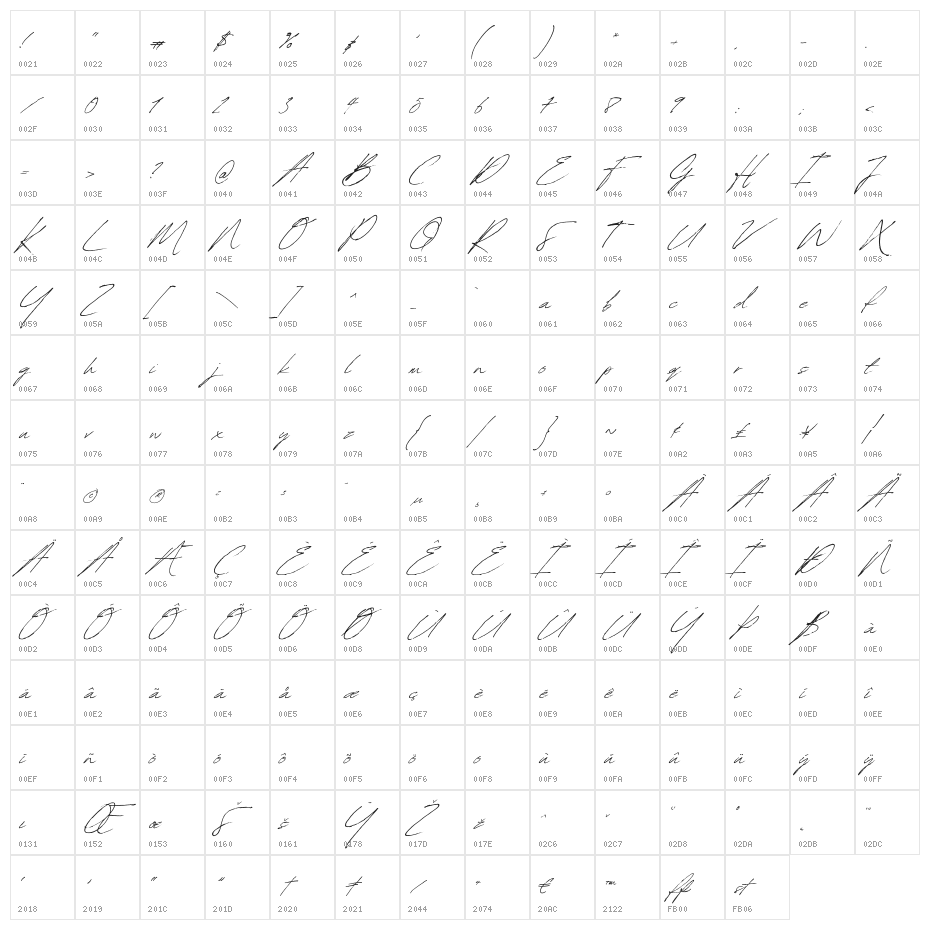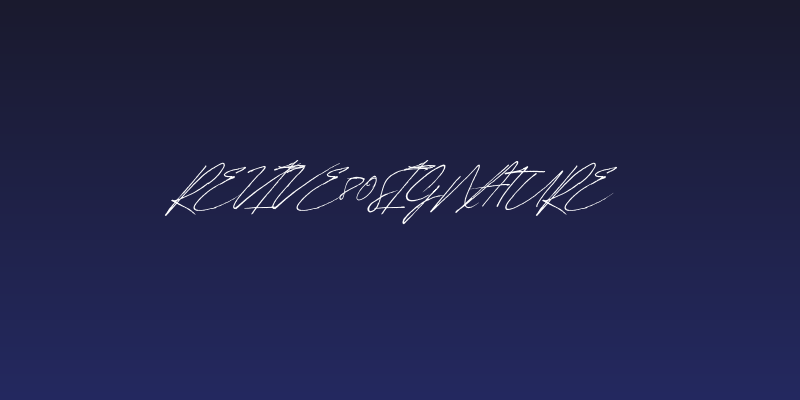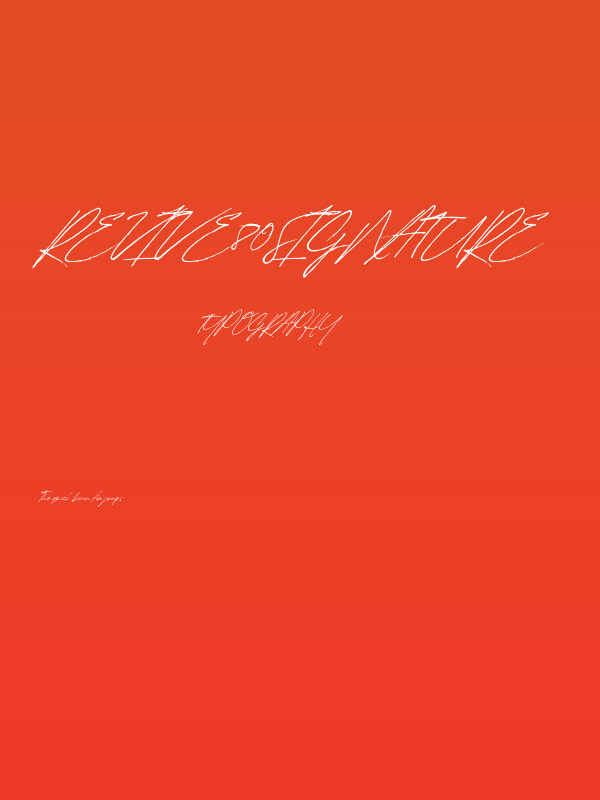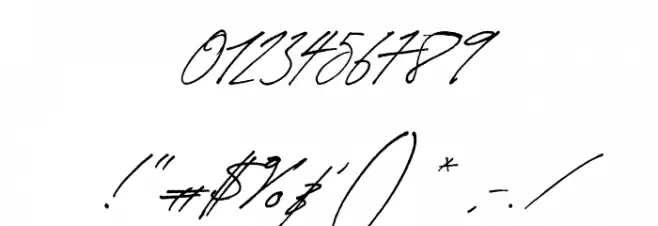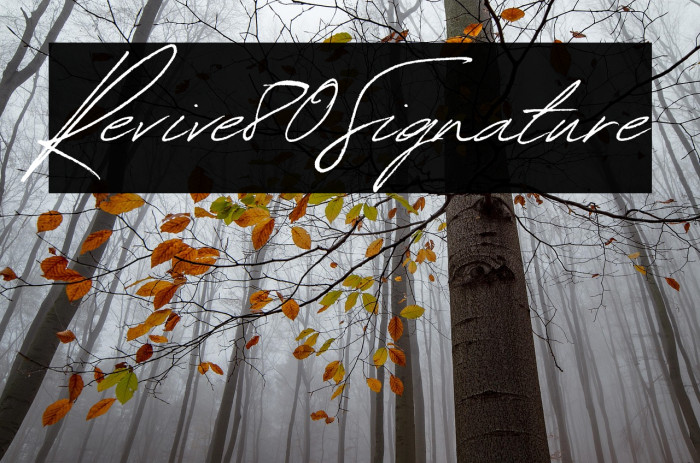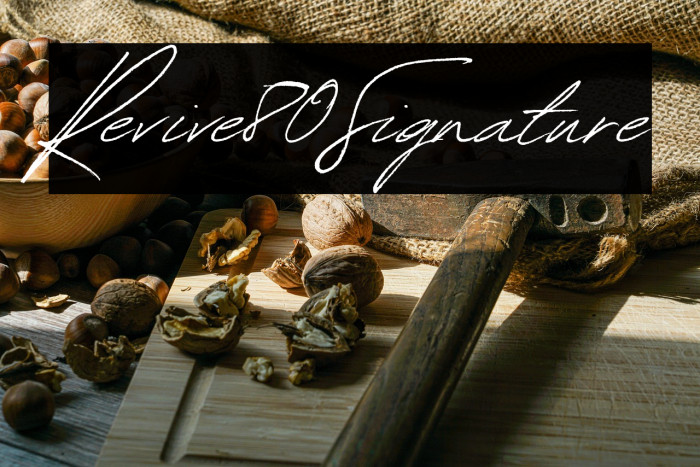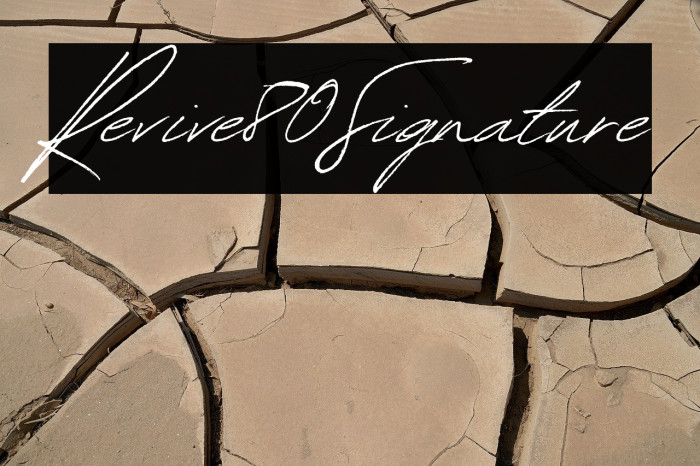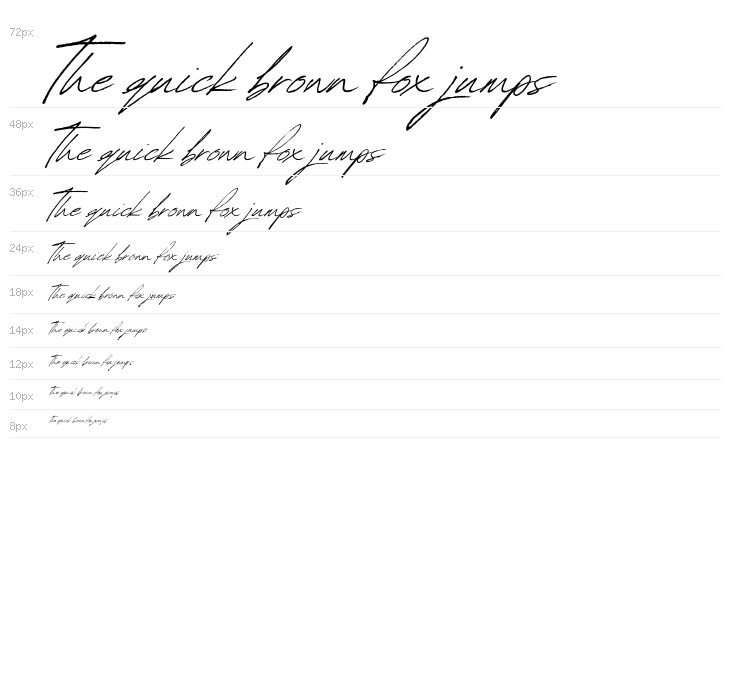
Revive80Signature Font
| Nome | Revive80Signature |
| Famiglia di caratteri | Revive 80 Signature |
| Peso | Signature |
| Stile generale | Elegant, Sophisticated, Handwritten |
| Caso d'uso | Logos, Invitations, Personal Branding |
| Progetti proposti | Ideal for wedding invitations, personal branding, elegant stationery, and artistic projects requiring a personal touch. |